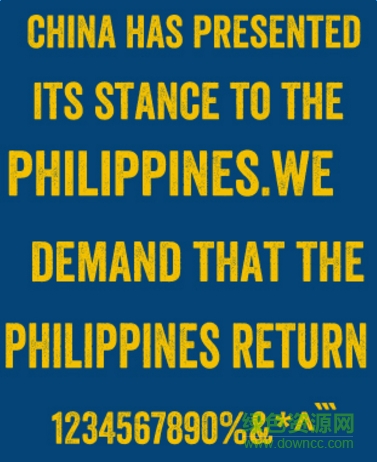
veneer字體是一款超好用的個(gè)性英文字體,該字體非常正式,適用于多個(gè)設(shè)計(jì)領(lǐng)域,對(duì)于廣告的宣傳效果更是有了極強(qiáng)的襯托效果。需要的朋友趕快來(lái)綠色資源網(wǎng)下載使用吧!
veneer字體是一款個(gè)性字體,該字體十分飄逸,彰顯了自己的個(gè)性,有喜歡的朋友可以來(lái)綠色資源網(wǎng)下載使用!